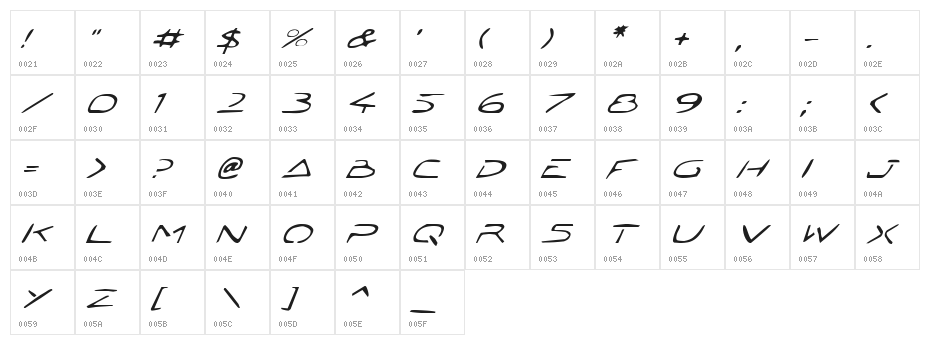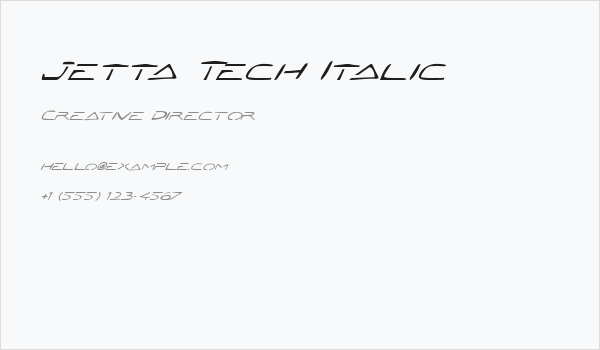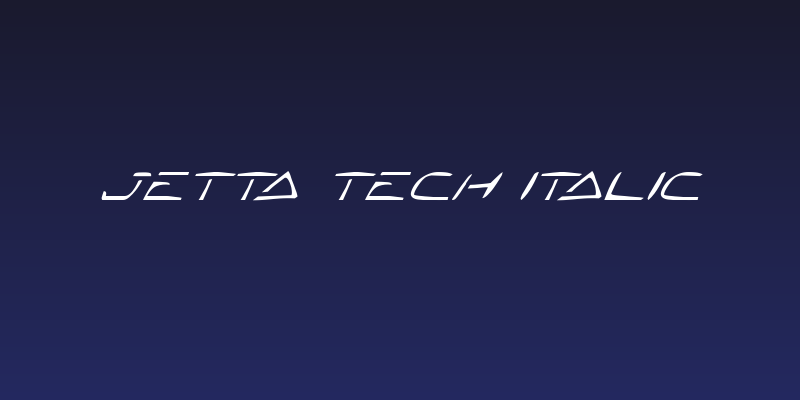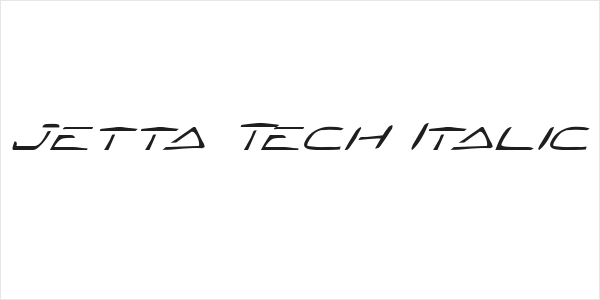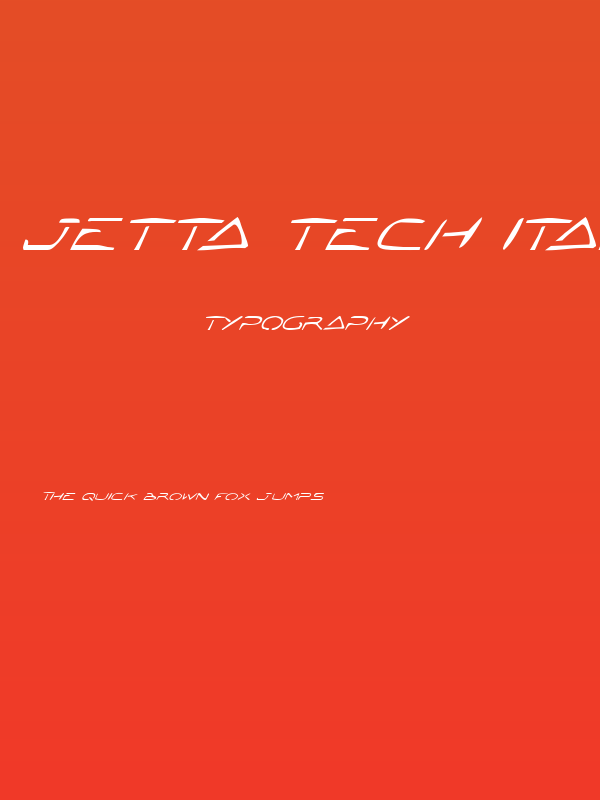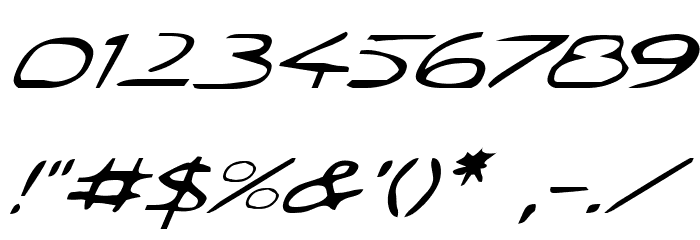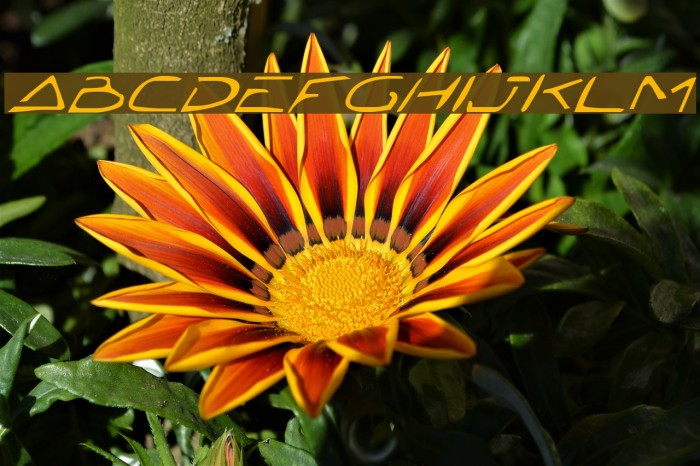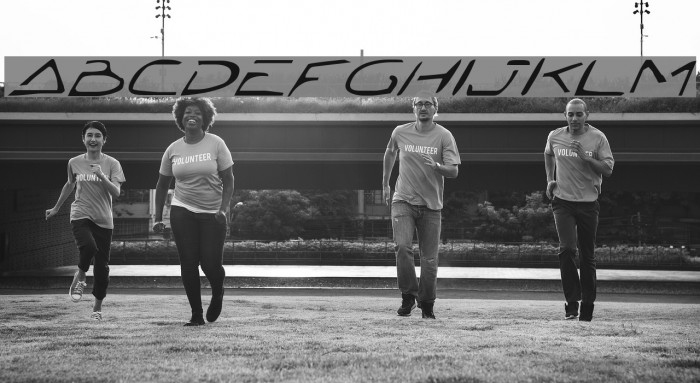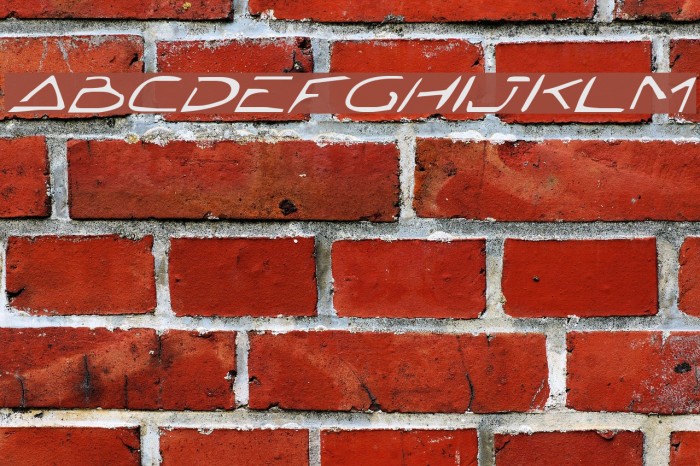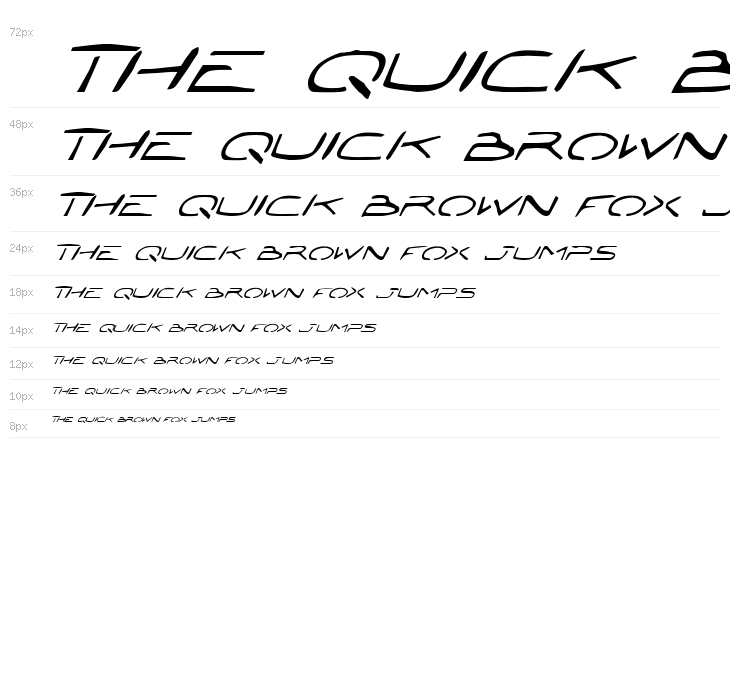
Jetta Tech Italic Font
| حالة الاستخدام | Logos, Headlines, Digital Interfaces |
| مشاريع مقترحة | Ideal for technology branding, automotive design, sci-fi themed projects, and modern digital interfaces. |